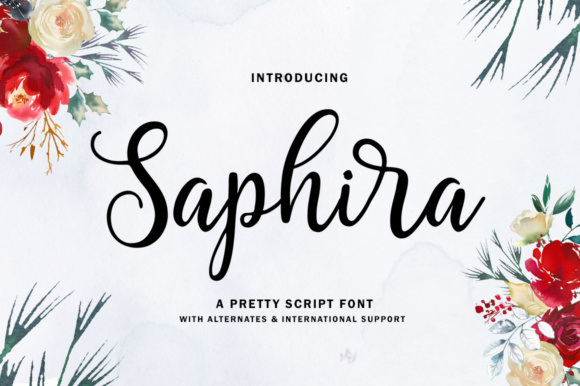
Saphira
หากคุณกำลังมองหาเนื้อหาคุณภาพสูงเช่น Saphira แพ็คเกจพรีเมียมนี้เป็นตัวเลือกที่ยอดเยี่ยมสำหรับโปรเจ็กต์สร้างสรรค์ของคุณ
ไม่ว่าคุณจะสร้างผลิตภัณฑ์ POD (Print on Demand) คำเชิญงานแต่งงาน หรือกราฟิกโซเชียลมีเดีย Saphira ก็เหมาะสมอย่างยิ่ง